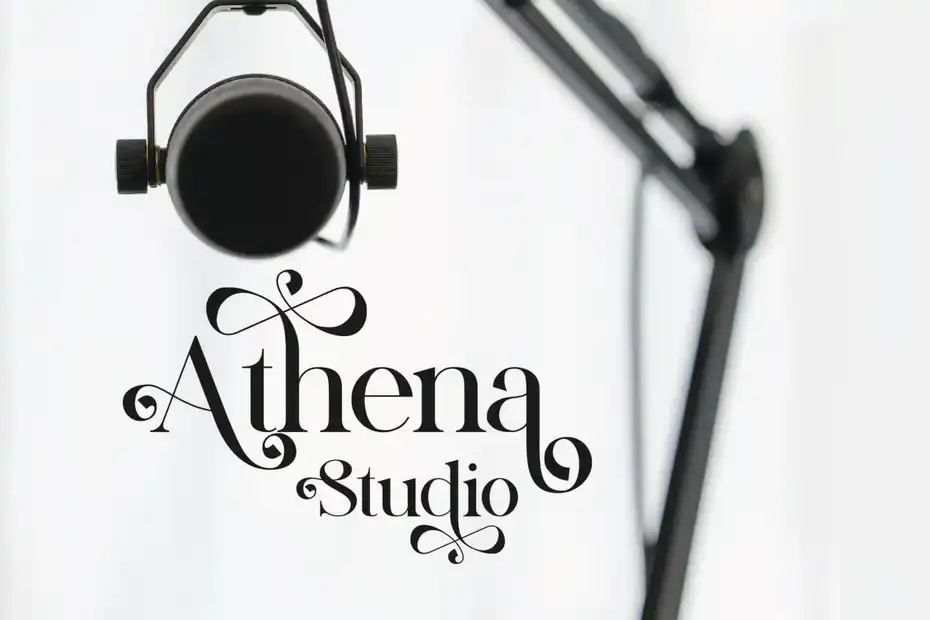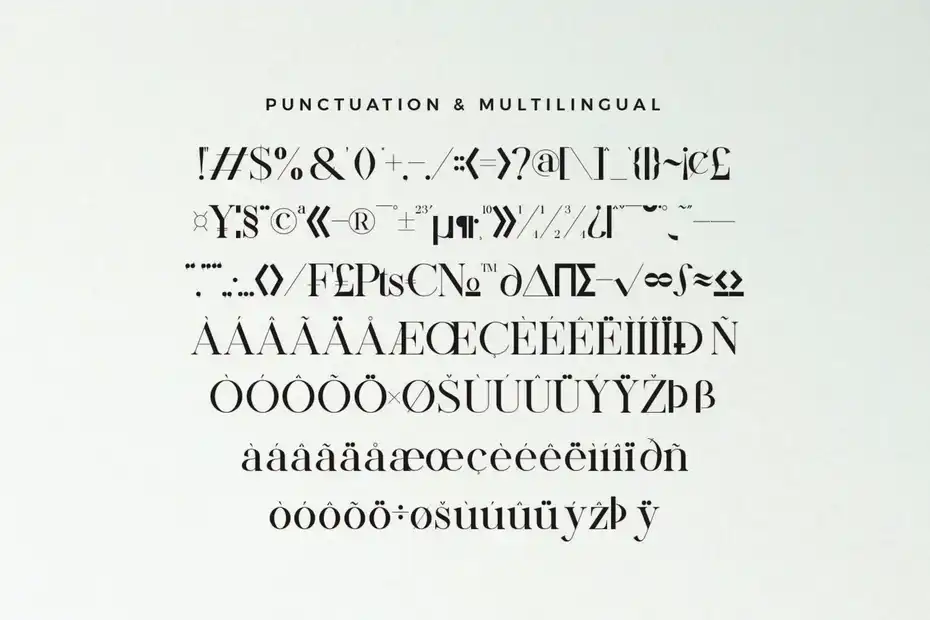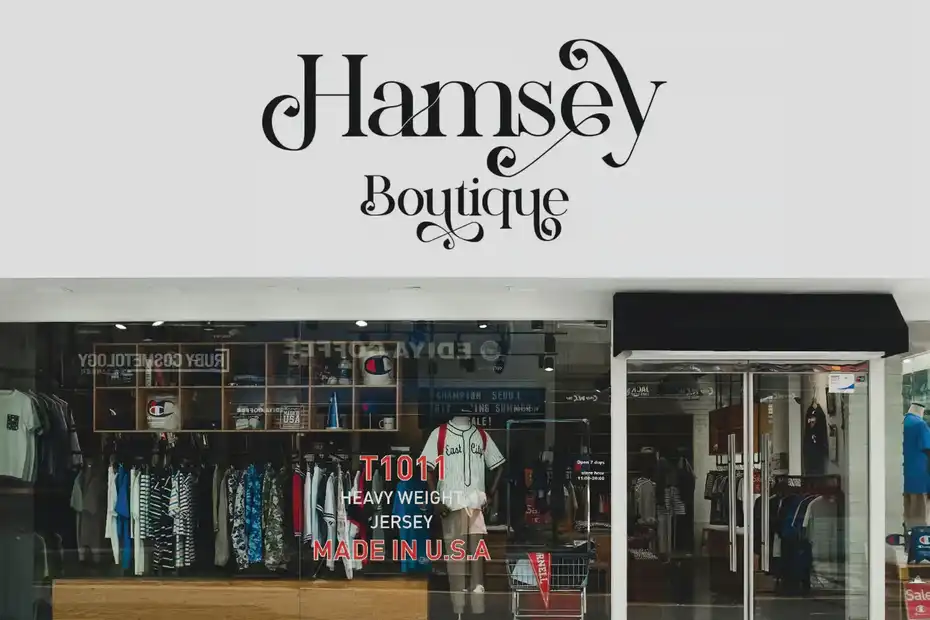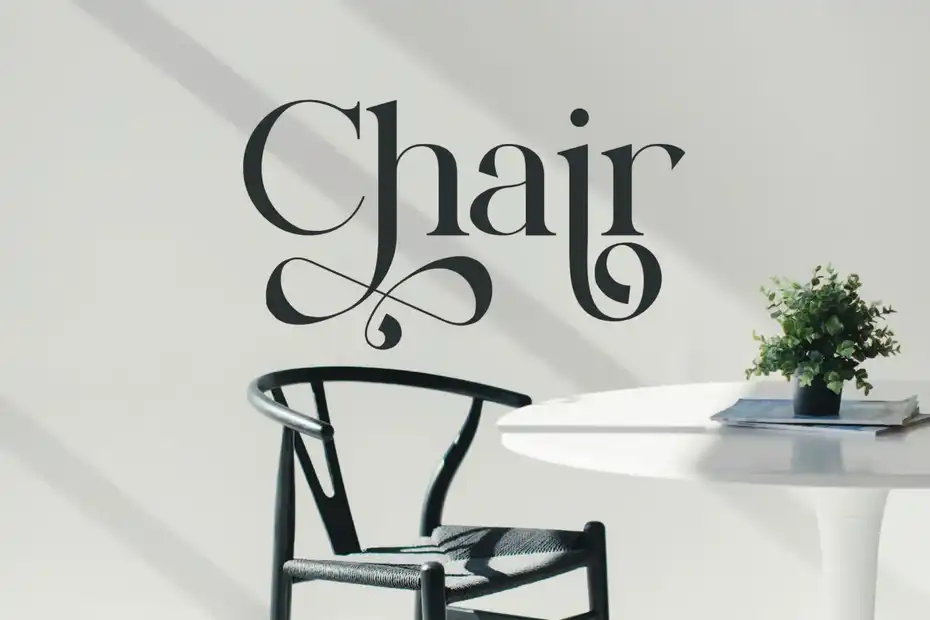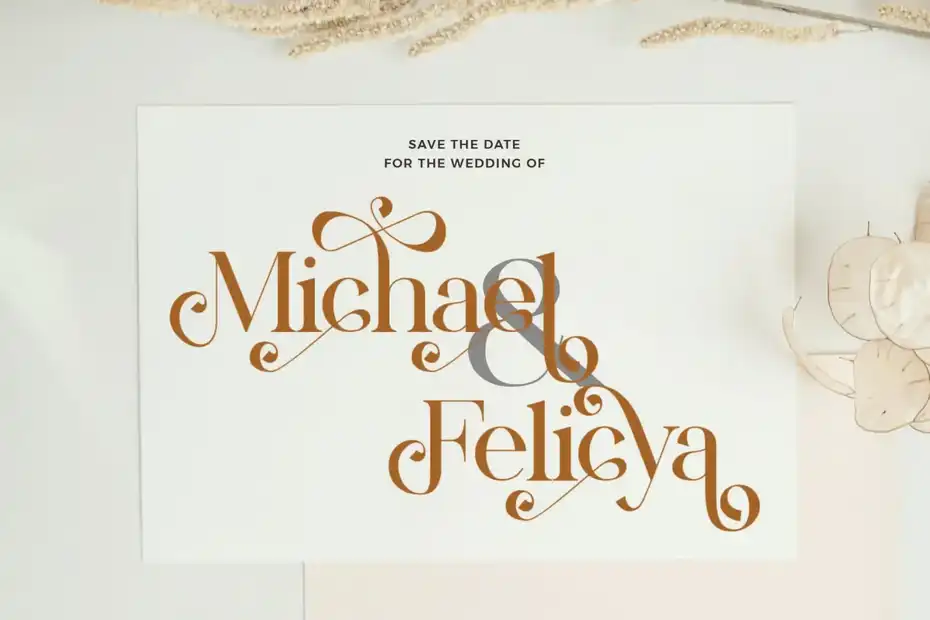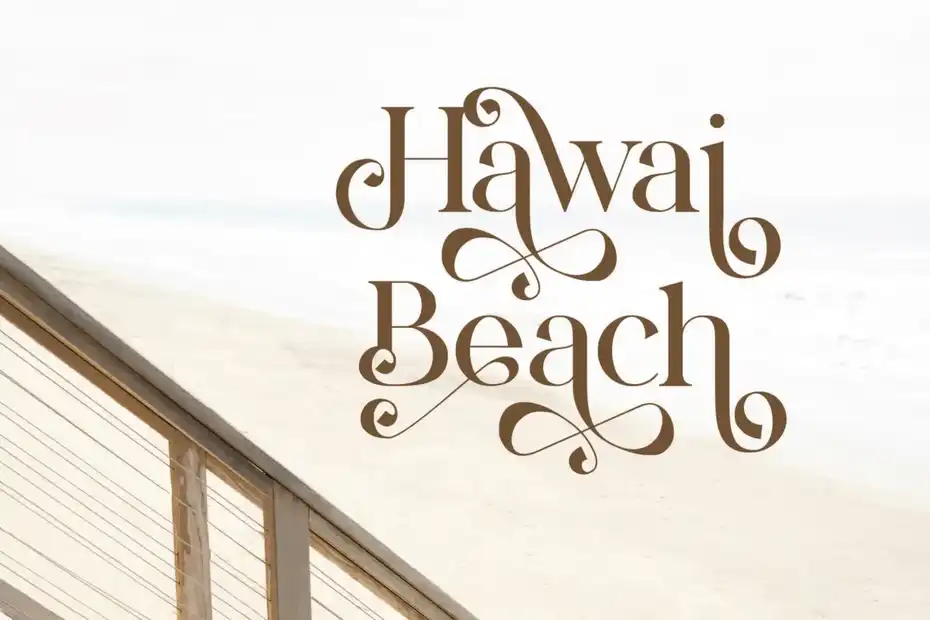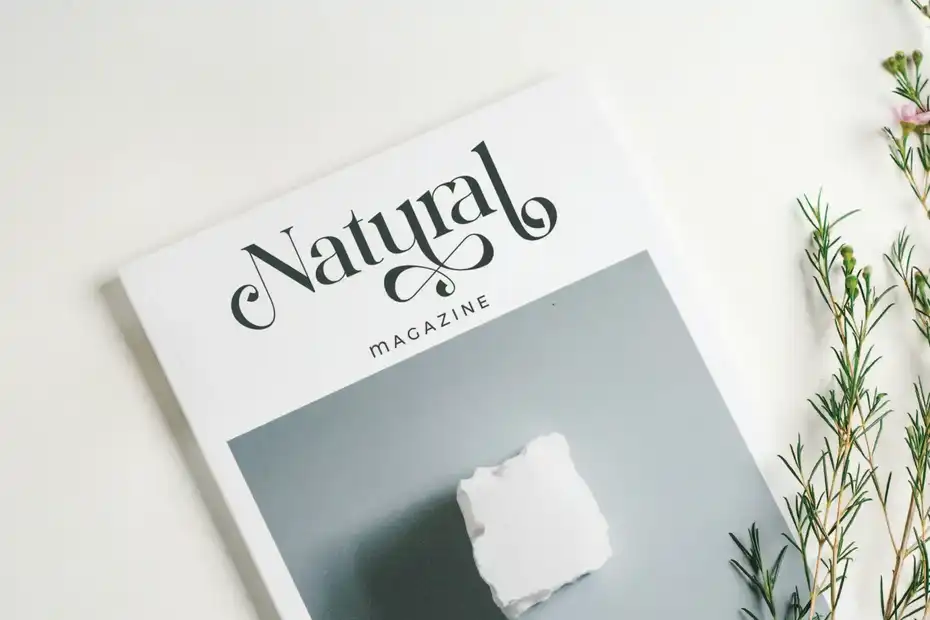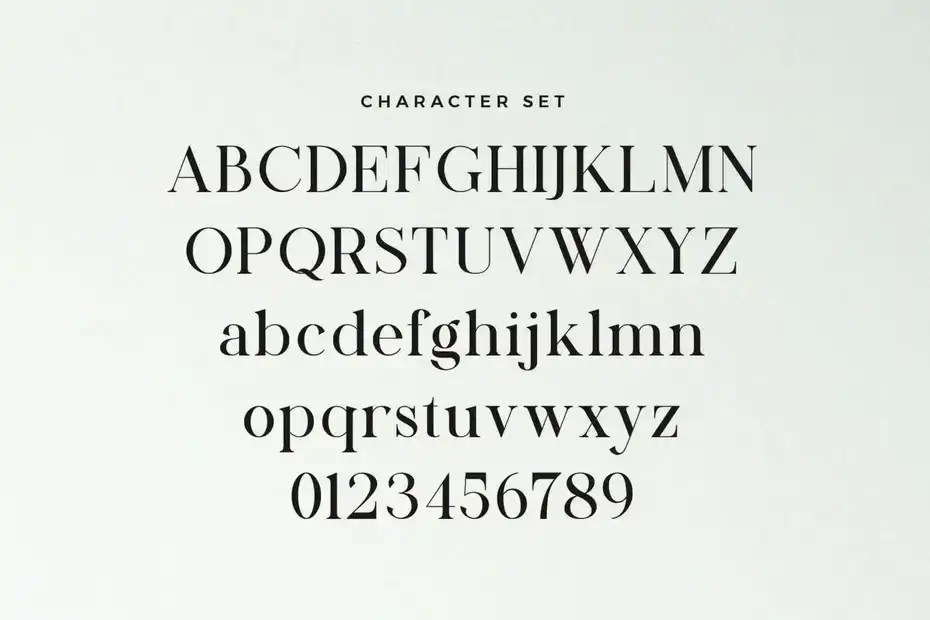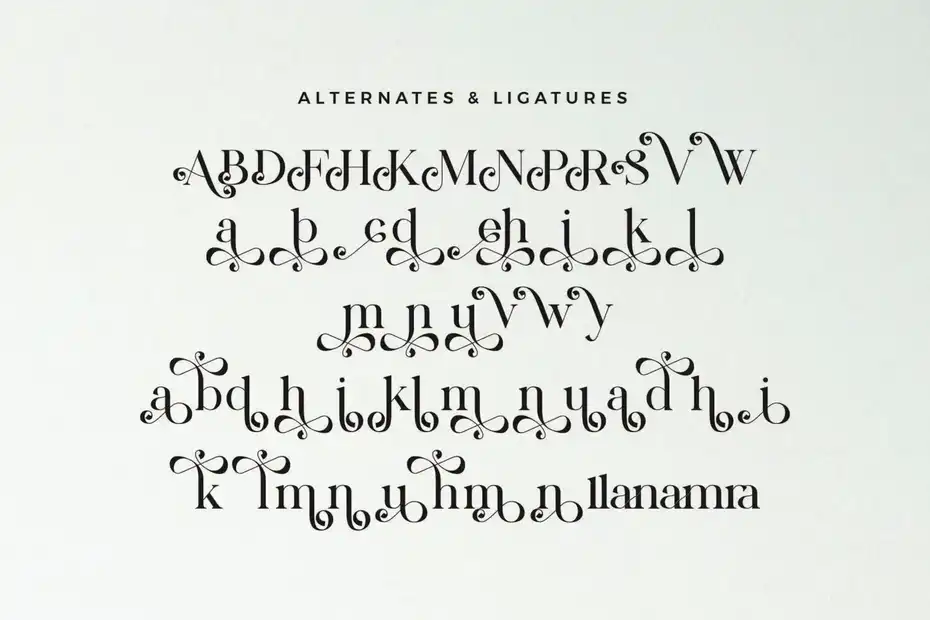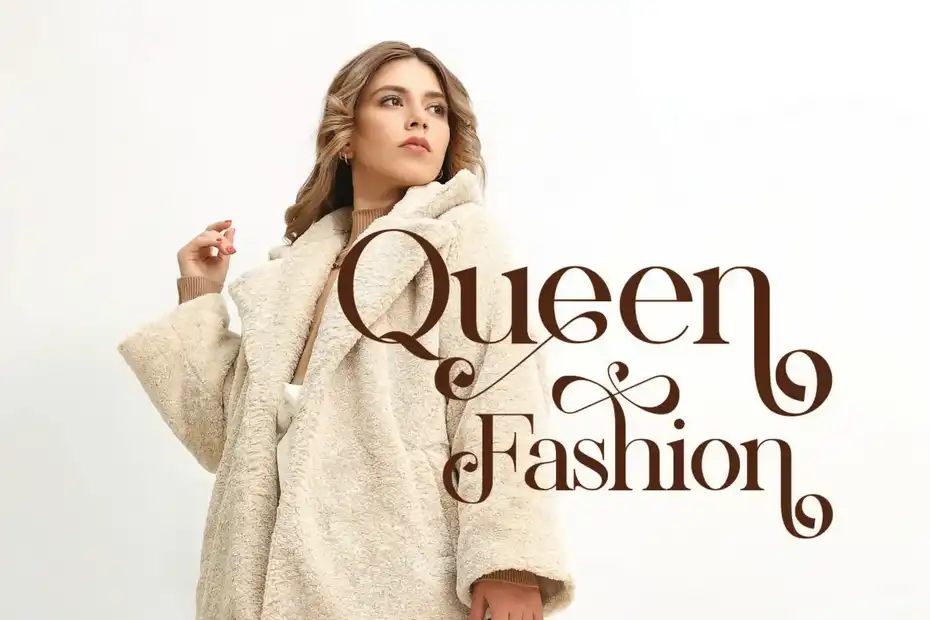
فونت انگلیسی کلاسیک Mackin – Beautiful Ligature Font : این مطلب شامل یک فونت انگلیسی کلاسیک است که برای لوگو، بروشور، ویدیو، برندسازی تبلیغاتی و غیره مناسب میباشد.
• عنوان مجموعه: Mackin – Beautiful Ligature Font
• سبک: Serif